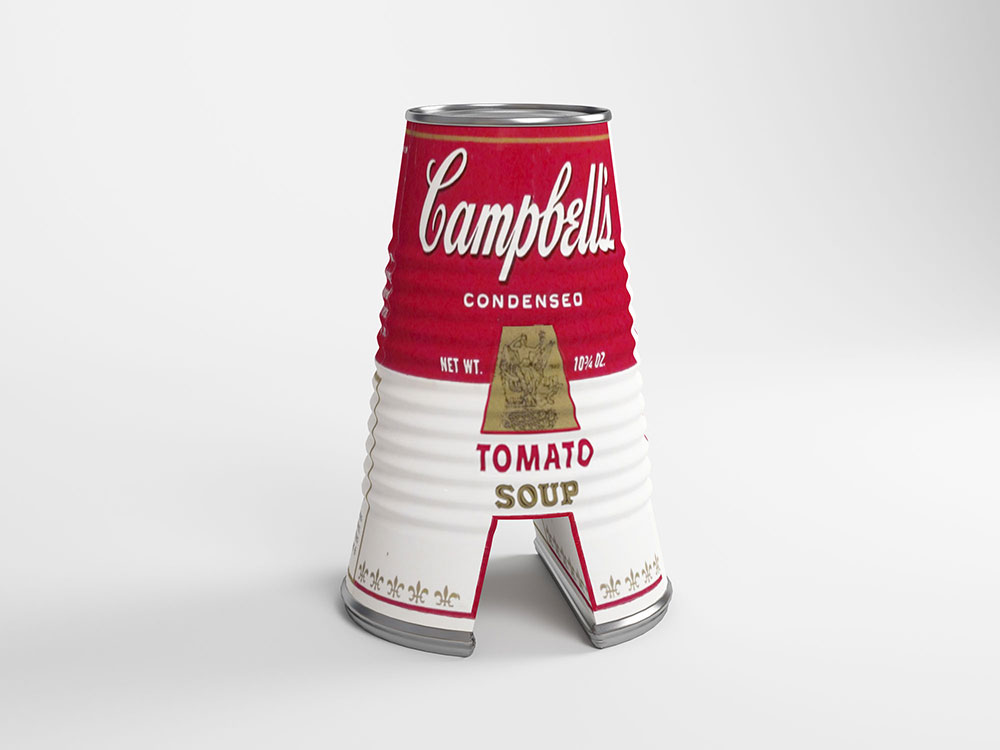
Una letra, un artista
El estudio de ilustración madrileño Cess es el responsable de The Artphabet, un alfabeto creado para homenajear a los principales artistas modernos y contemporáneos. El proyecto fue presentado en la última edición del 36 Days of Type, el reto en el que participan miles de diseñadores de todo el mundo, y que consiste en presentar un diseño nuevo cada día durante los 36 días que dura el reto. The Artphabet consiguió ser una de las propuestas más llamativas gracias a sus 26 letras que permiten identificar rápidamente a los mundialmente reconocidos artistas a los que representan. Warhol, Banksy, Frida Kahlo, Picasso, Van Gogh o Gaudí son sólo algunos de los artistas a los que el estudio Cess ha homenajeado a través de esta serie tipográfica diseñada en 3D.